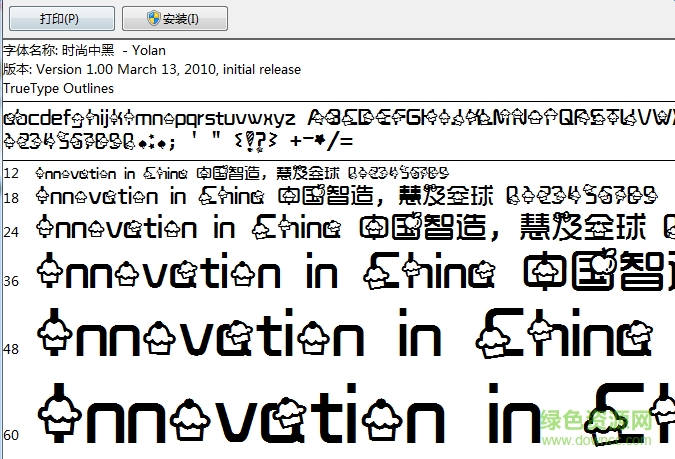
生日快樂字體是一款應(yīng)用于生日設(shè)計(jì)方面的字體,該字體非常具有個(gè)性,可廣泛應(yīng)用于平面設(shè)計(jì)、廣告設(shè)計(jì)、報(bào)紙雜志、正文標(biāo)題等領(lǐng)域,喜歡的網(wǎng)友可免費(fèi)下載收藏。
生日快樂字體是一款極具個(gè)性的字體,該字體能夠讓人聯(lián)想到生日蛋糕,非常具有童心化。有喜歡的朋友可以來綠色資源網(wǎng)下載使用!